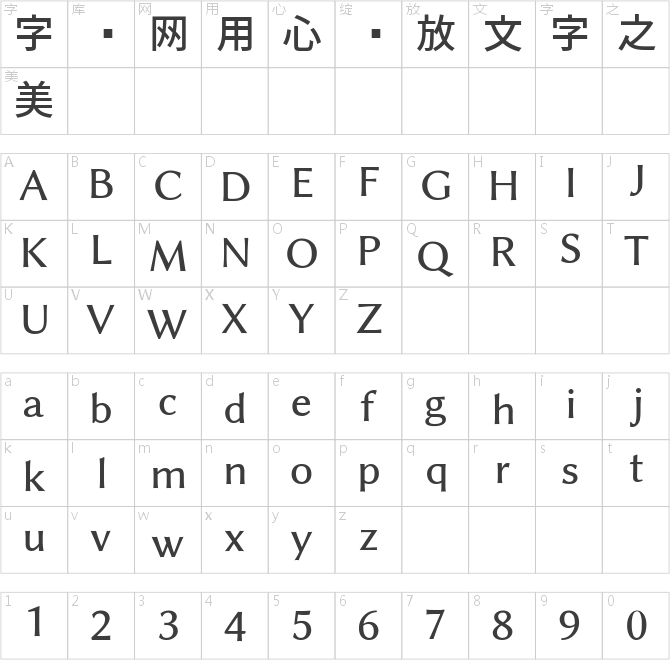
源暎漫畫體字體下載GenEiLateMin
源暎漫畫體是以日本版的思源黑體Semibold為基礎,參考Light字重制作了平假名和片假名。因為骨骼來源于黑體字,所以在漫畫臺詞中混合使用思源黑體、源真黑體等字體也可以毫無違和感地使用。這款字體削減了橫筆的粗細,使字體看上去更具現(xiàn)代感。特別適合用于海報標題,LOGO等方面的設計。因為這個字體以面向漫畫為主要用途,所以主要是與反映出的黑體漢字組合而成的“源暎漫畫體”。